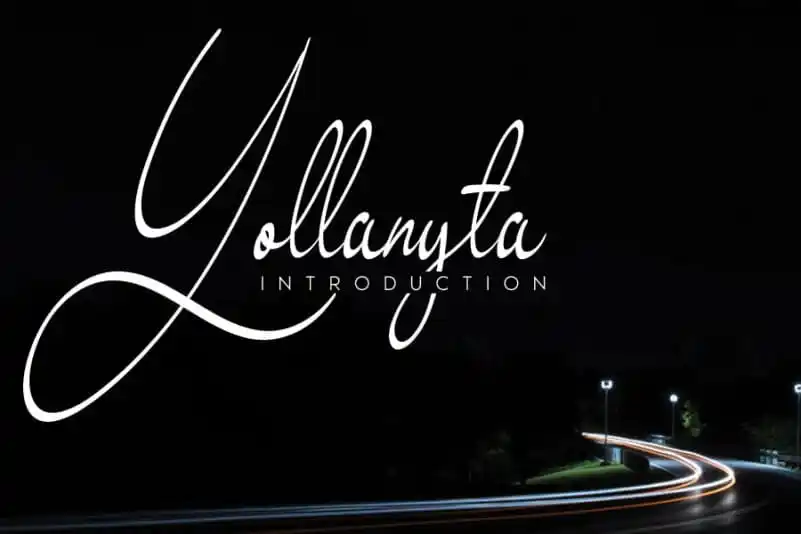
Yollanyta Handwritten Font – Download Grátis
A Yollanyta Handwritten Font é uma elegante e fluida tipografia escrita à mão que carrega consigo um charme singular desde a primeira impressão. Suas linhas relaxadas e delicadamente cuidadosas proporcionam um toque único de sofisticação, tornando-a perfeita para qualquer projeto de design imaginável. Se você é amante do estilo de escrita à mão, Yollanyta se tornará um elemento indispensável em seu arsenal de fontes. Suaviza e enriquece suas criações com uma dose de personalidade autêntica que fará sua obra sair acima dos demais.